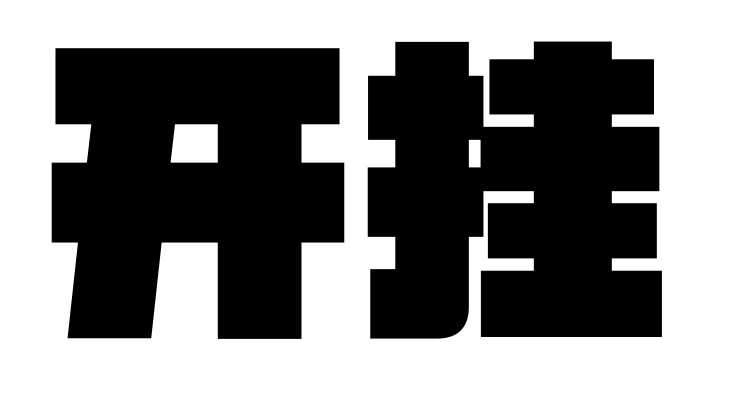
在游戏里开挂是一种什么体验?竞技类游戏字体——励字铁拳简给你答案
科幻竞技类游戏习惯已有的东西推向极端,经常夸张化字体硬角或压平曲线,饱满的字面以及粗壮的笔画也是常用的手段之一。让人感觉字体就好像是计算机自动生成的,满足我们对未来的一切想象。
励字铁拳简,一款创意黑体字,笔画粗壮、字面宽大,饱满的块面感以及折角圆设计,视觉冲击强烈,犹如铁拳出击,横扫千军。
用好字体才能获得胜利!不管是平面、游戏、UI又或者是三维,或多或少都会使用到字体的设计,作为表达的工具,它和地心引力一样强大,使用开挂字体,给游戏体验加载强大动力~